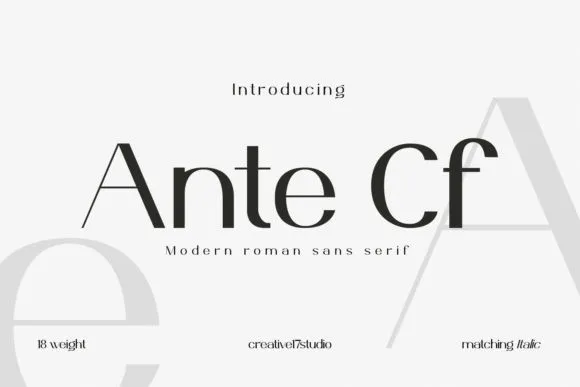
Ante Cf Sans Serif Font
Esta é uma fonte sans serif que foi criada pela Creative17studio. Ante Cf Sans Serif oferece um estilo limpo e simples, perfeita para criar designs modernos e bem estruturados. Com mais de 18 pesos disponíveis, você tem a opção ideal para qualquer projeto que seja necessário se adaptar à necessidade específica do design. As diferenças notáveis entre os traços grossos e finos dão ao Ante Cf Sans Serif um toque único e personalizado. Este é o tipo de fonte perfeita para designers gráficos e web designers que buscam adicionar uma pegada moderna e elegante a seus projetos.